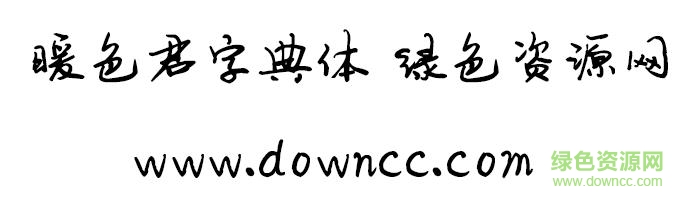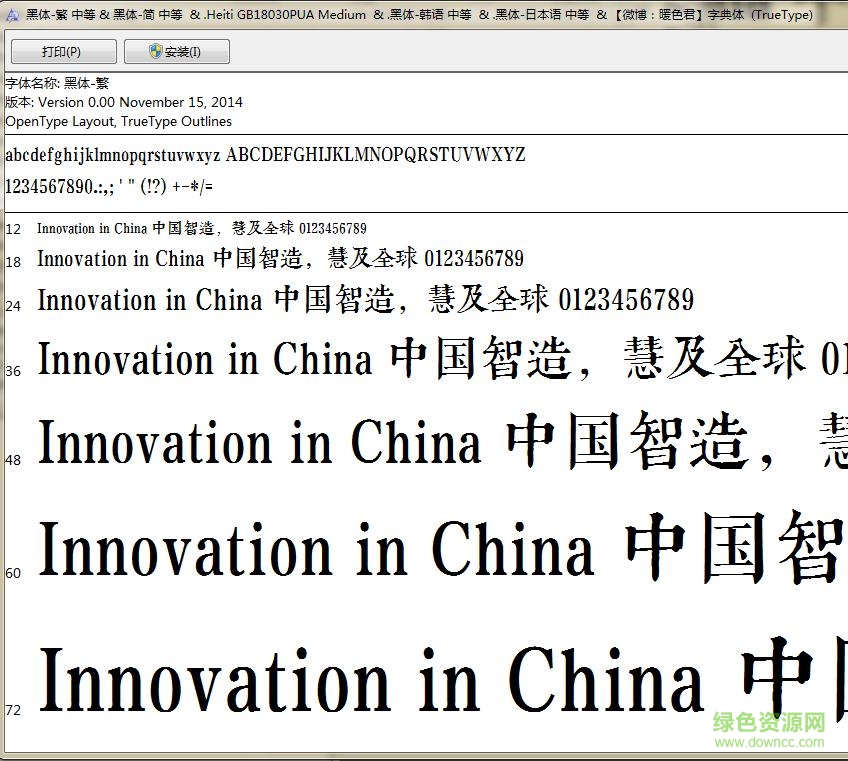
暖色君字典體ttf
暖色君字典體字體ttf是一款擁有讓你能夠一眼喜愛上的獨(dú)特風(fēng)格的字體,擁有如字典字體般的視覺效果,讓你查看每一個(gè)字都規(guī)規(guī)整整,能夠運(yùn)用到眾多書籍中進(jìn)行文字閱讀!
暖色君字典體字體最大的特色在于擁有如字典閱讀般的體驗(yàn),對(duì)于用戶們的視覺是一種獨(dú)家的欣賞效果,讓你仿若觀看每一盤文章都猶如查看字典!